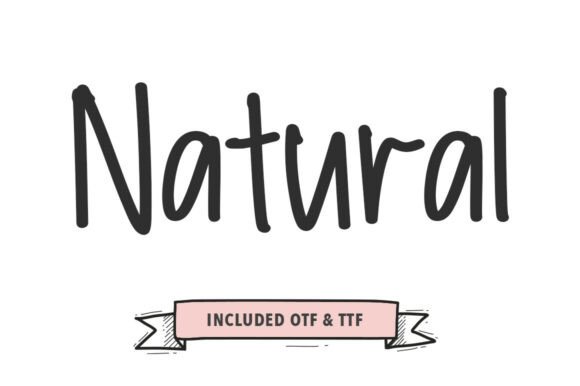
Natural Font
Die richtigen Designelemente zu finden, kann eine Herausforderung sein, aber Natural Font bietet eine außergewöhnliche Sammlung, die Ihre Arbeit sofort aufwertet.
Egal, ob Sie POD-Produkte (Print on Demand), Hochzeitseinladungen oder Social-Media-Grafiken erstellen, Natural Font ist die ideale Wahl.